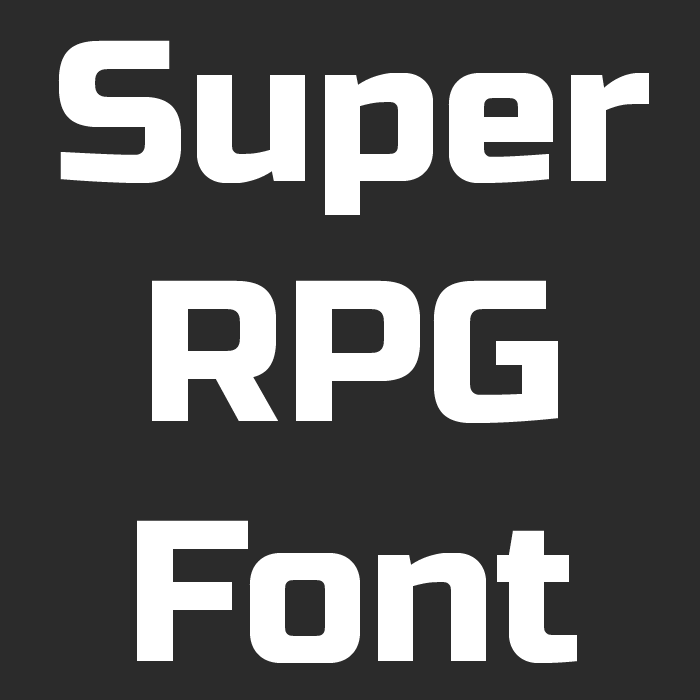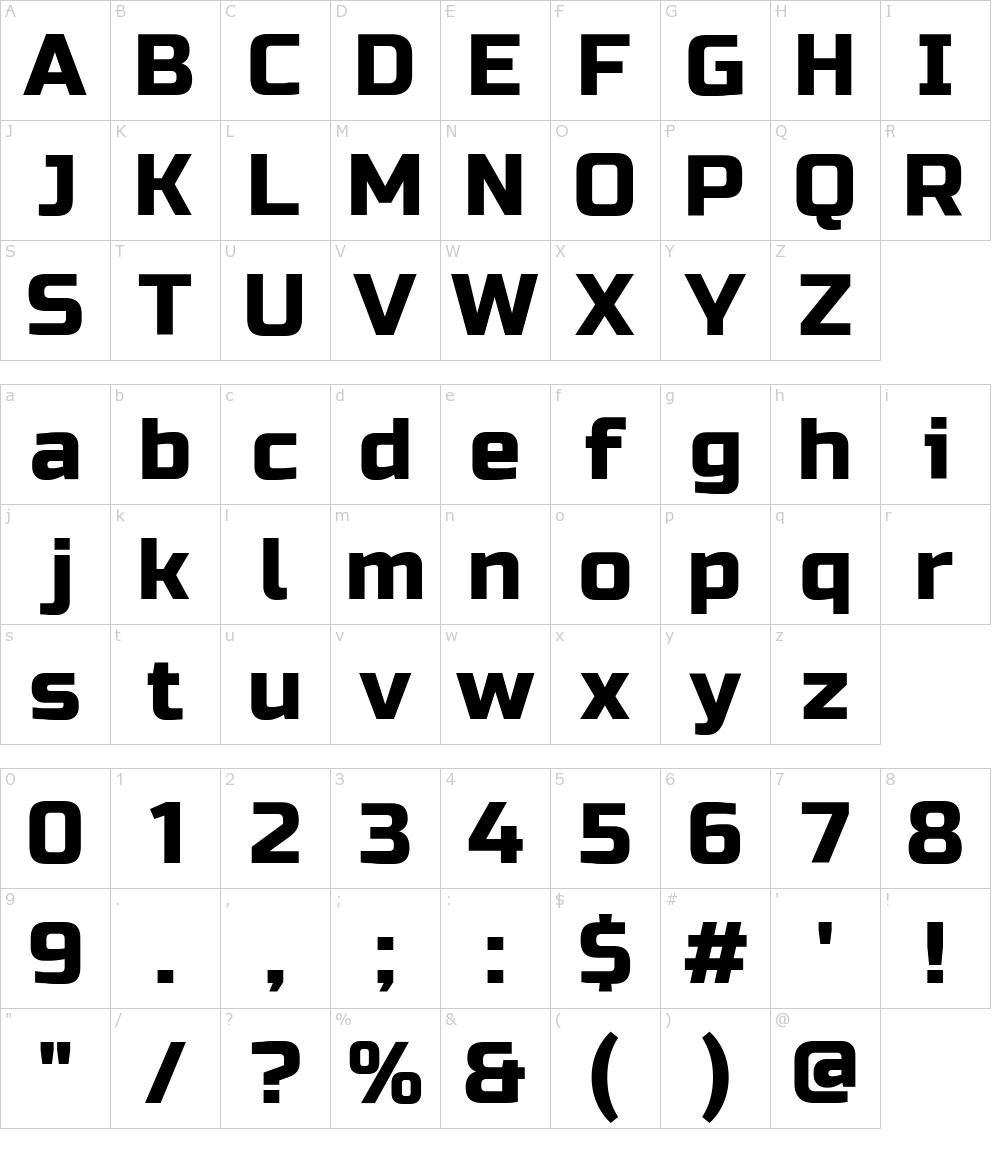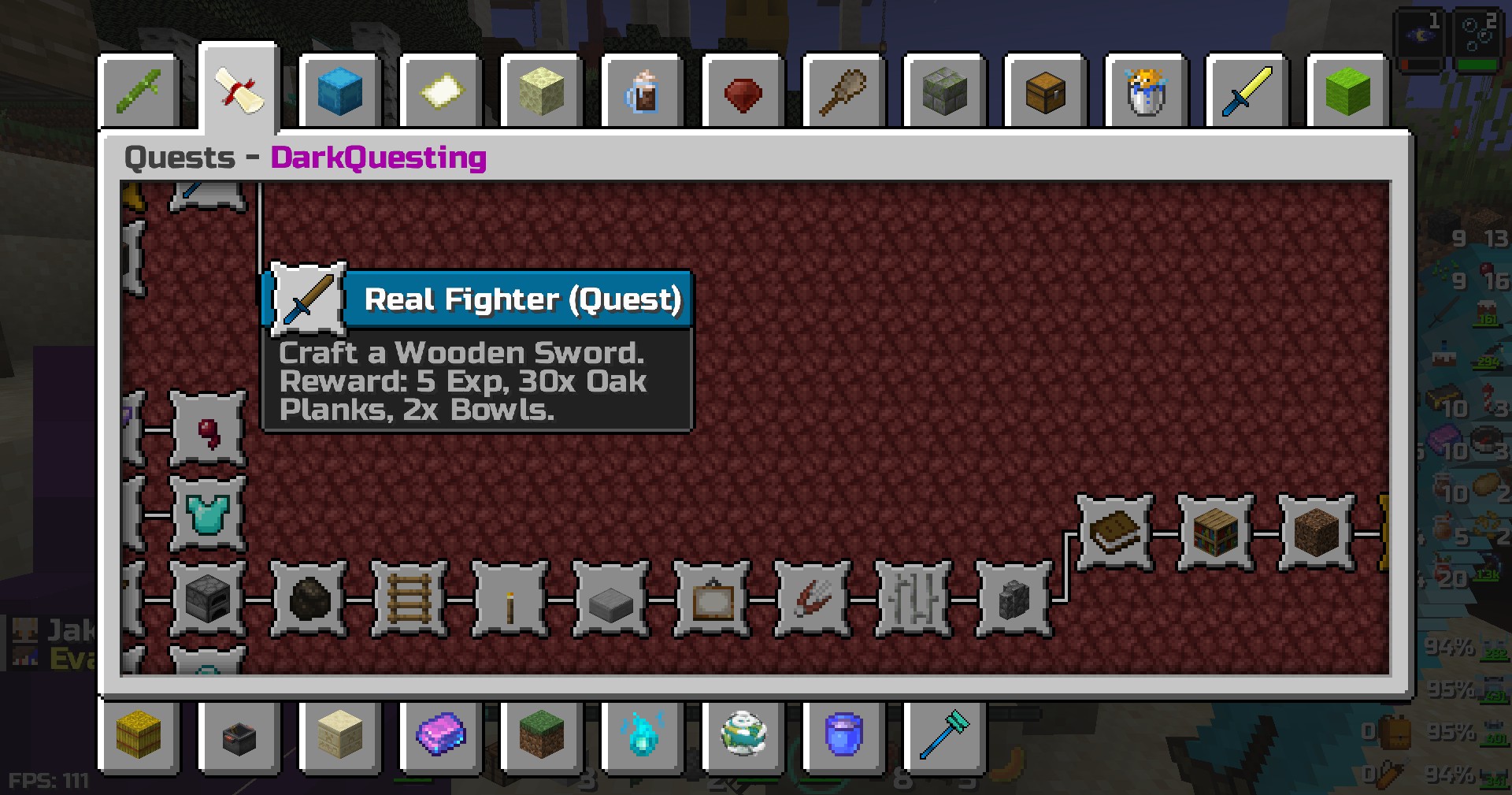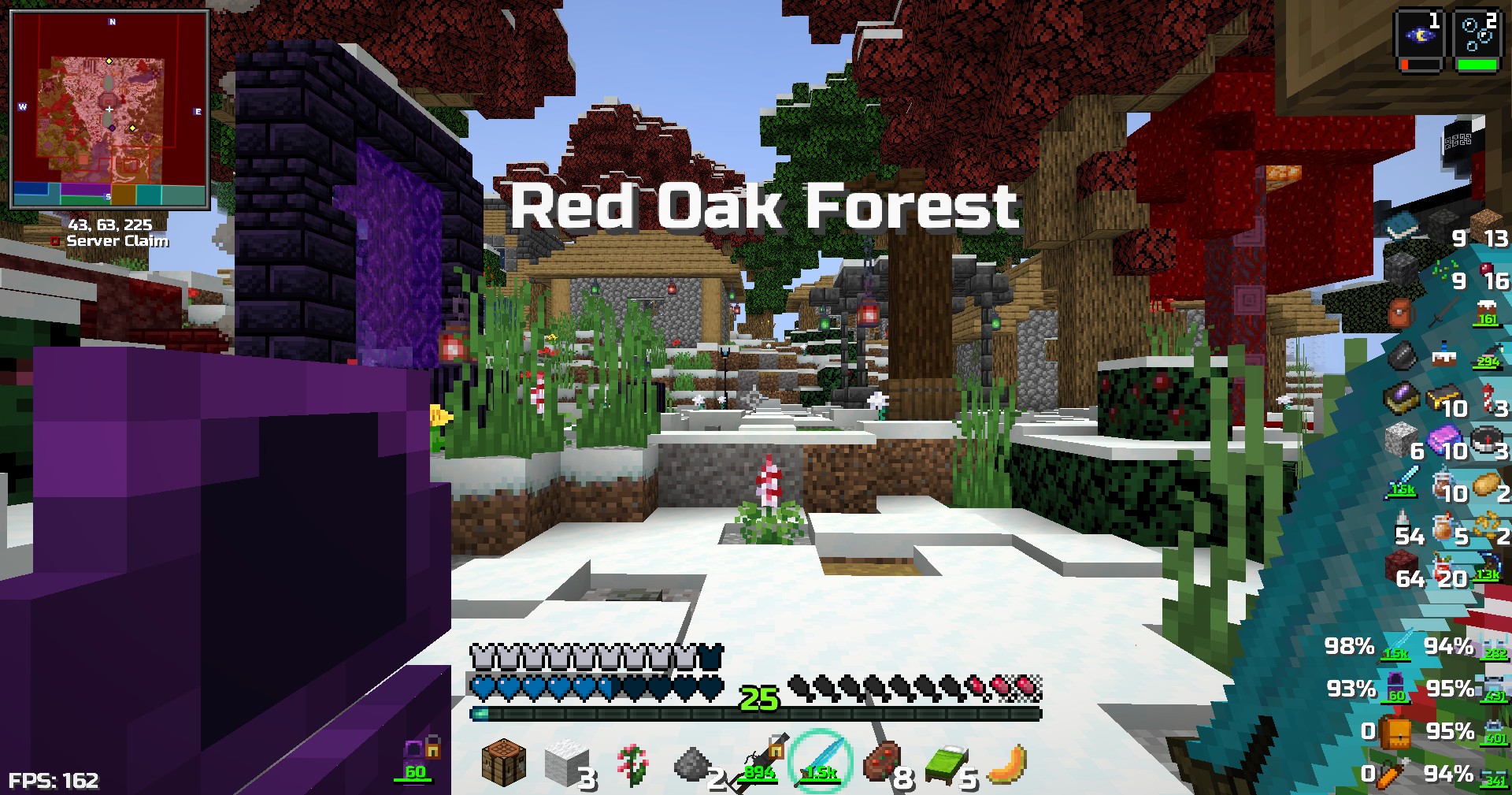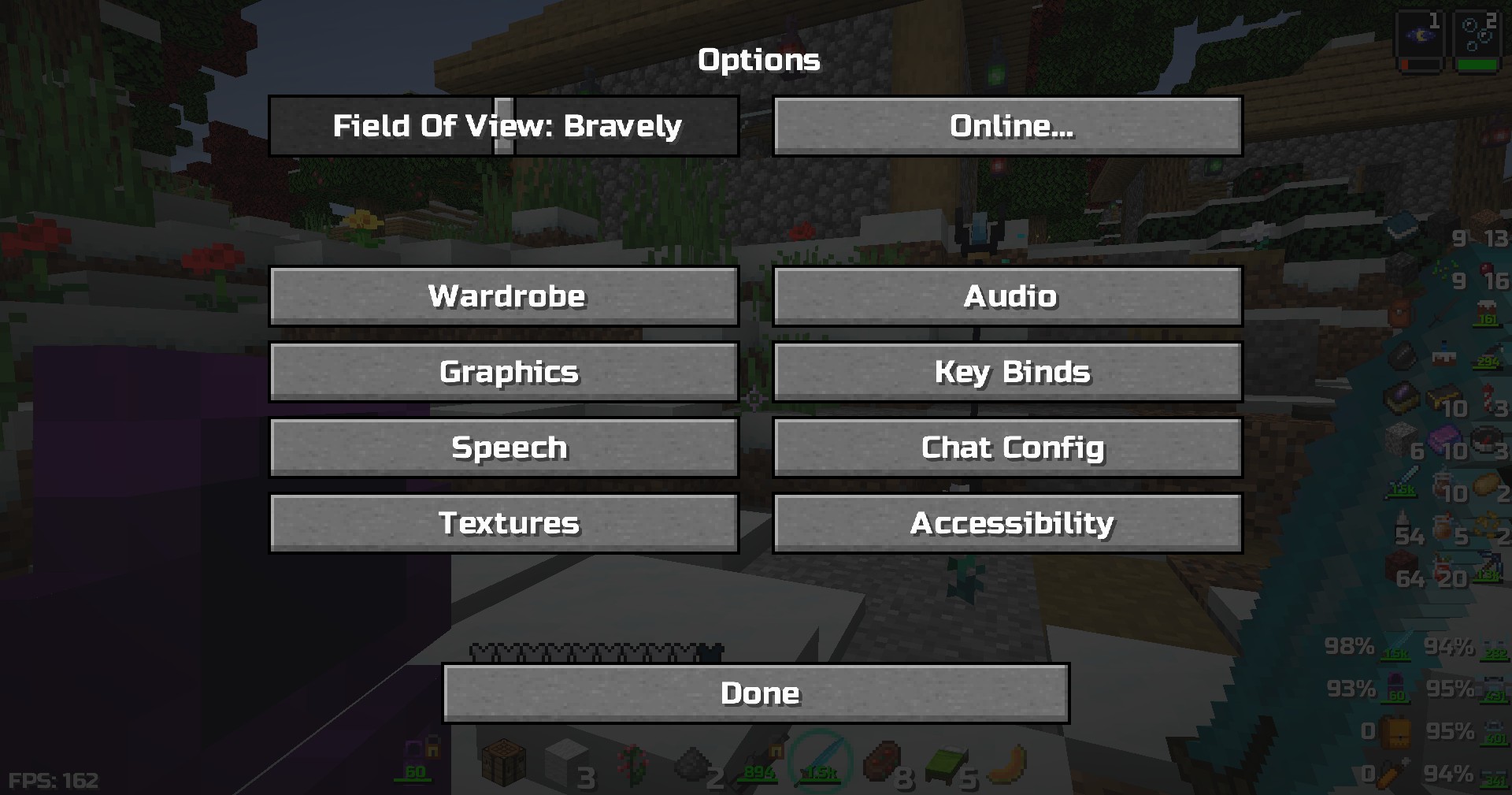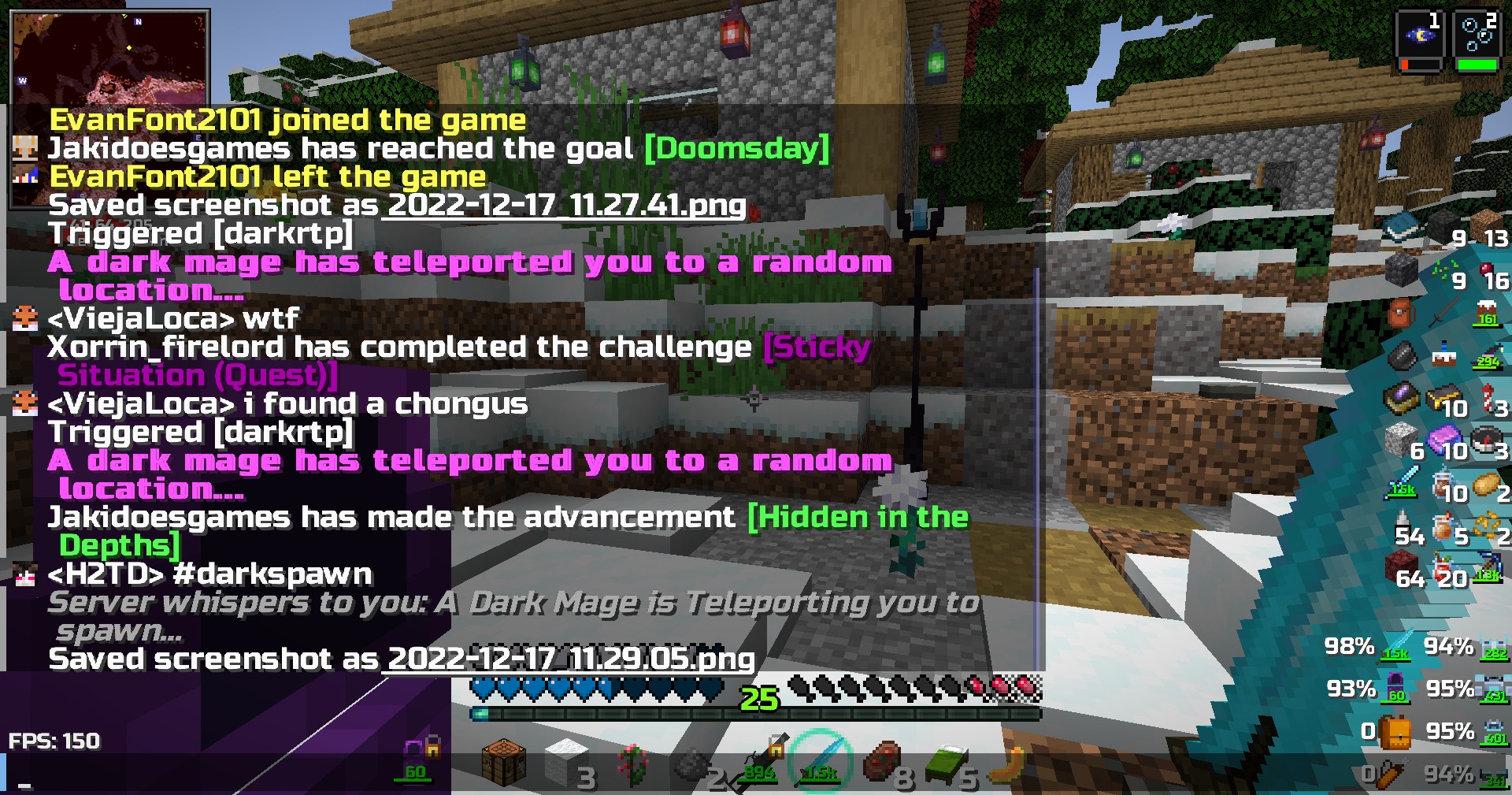
Современный и читабельный шрифт для вашего игрового процесса.
Мод Super RPG Font привносит новое восприятие текста в мир Minecraft, улучшая ваш опыт игры с помощью современного и стильного шрифта. Этот уникальный шрифт, созданный на основе популярного Russo One от Jovanny Lemonad, отличается превосходной читабельностью и эстетикой, что делает его идеальным выбором для любых игровых ситуаций.
Если вы ищете способ сделать ваш мир Minecraft более привлекательным и удобным, то мод Super RPG Font — это именно то, что вам нужно. Улучшите свои игровые взаимодействия, добавив стильный шрифт, который совместим с вашим любимым модпаком. Погружение в атмосферу RPG станет еще более увлекательным благодаря новому стилю отображения текста!